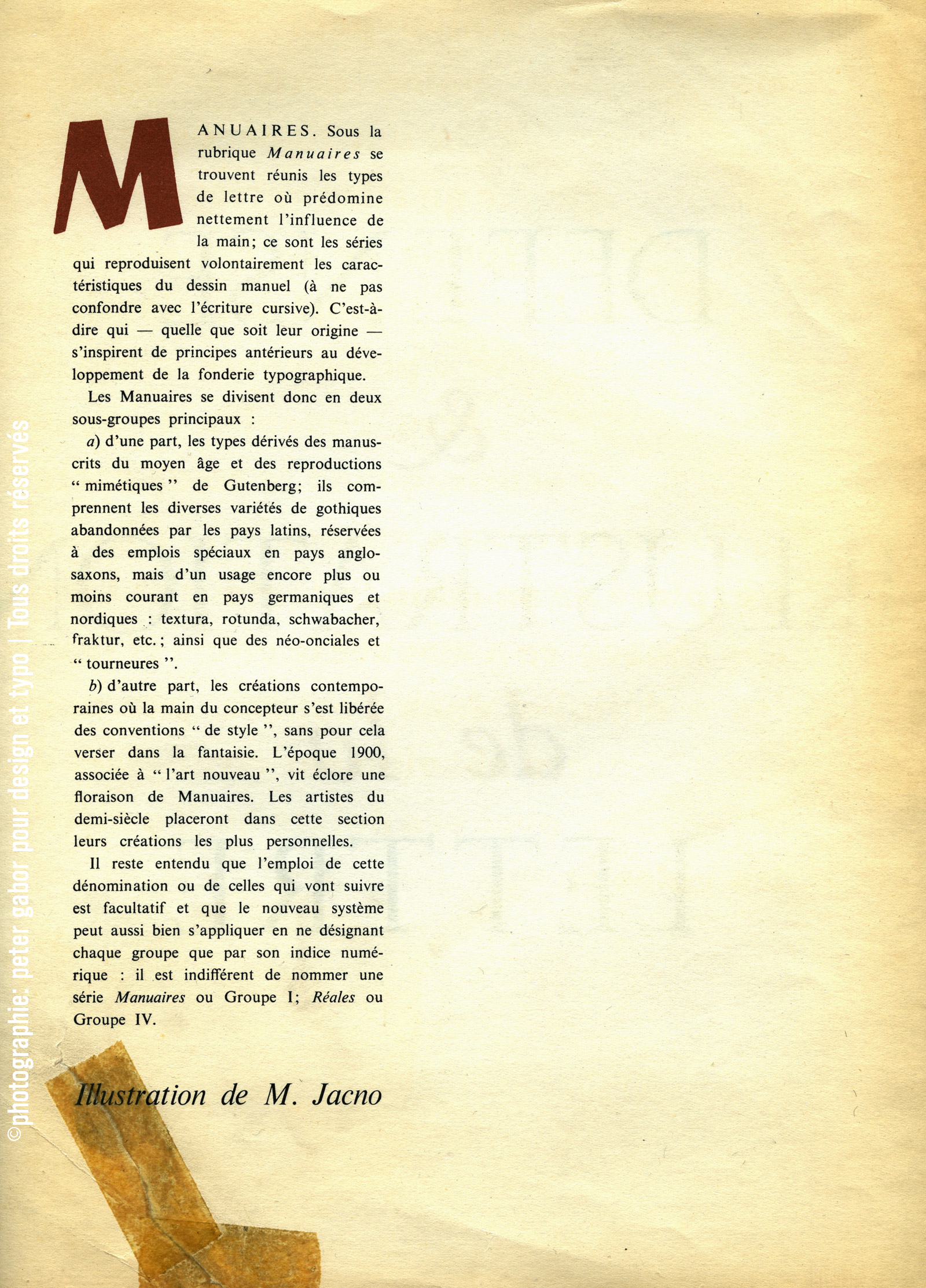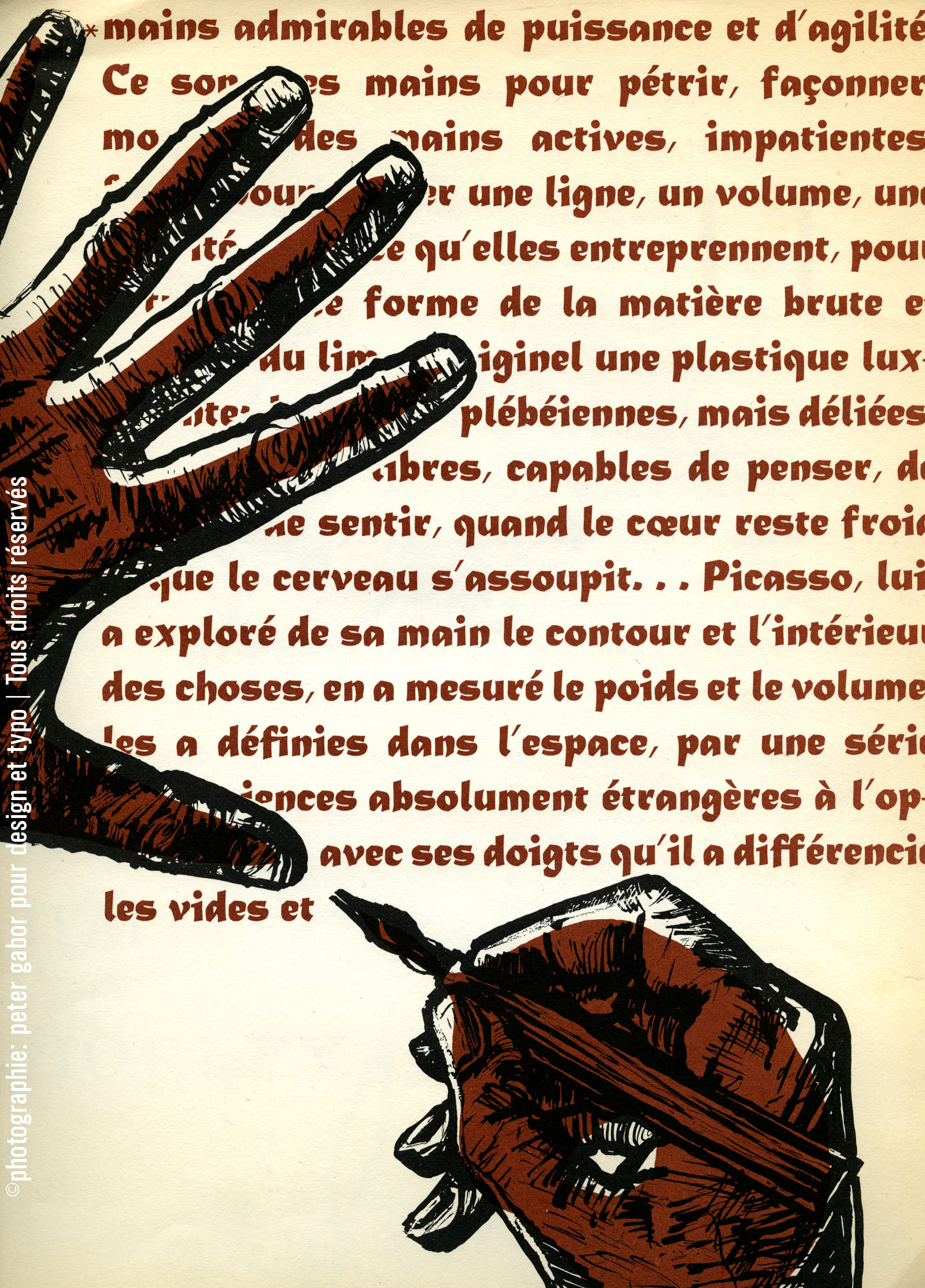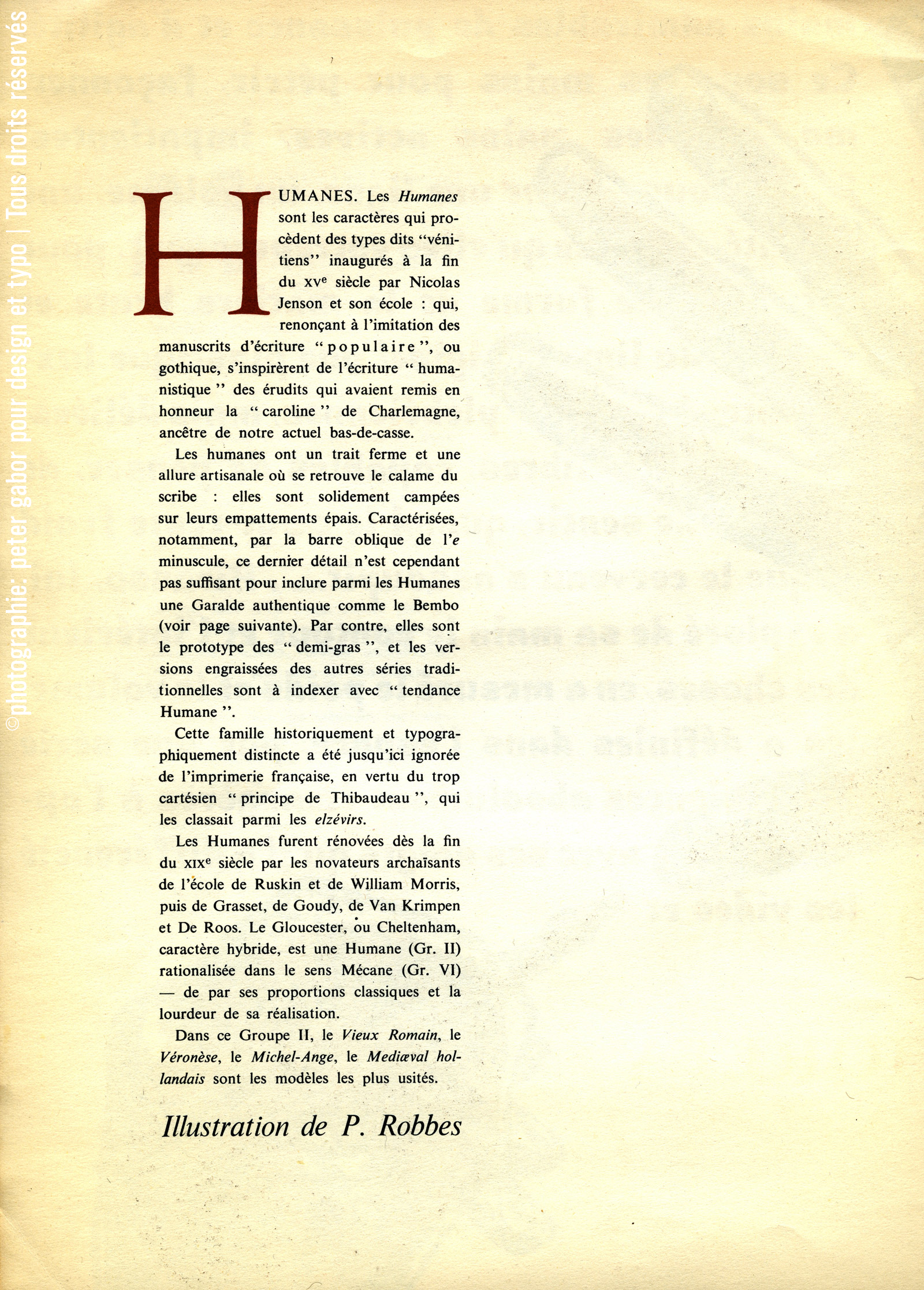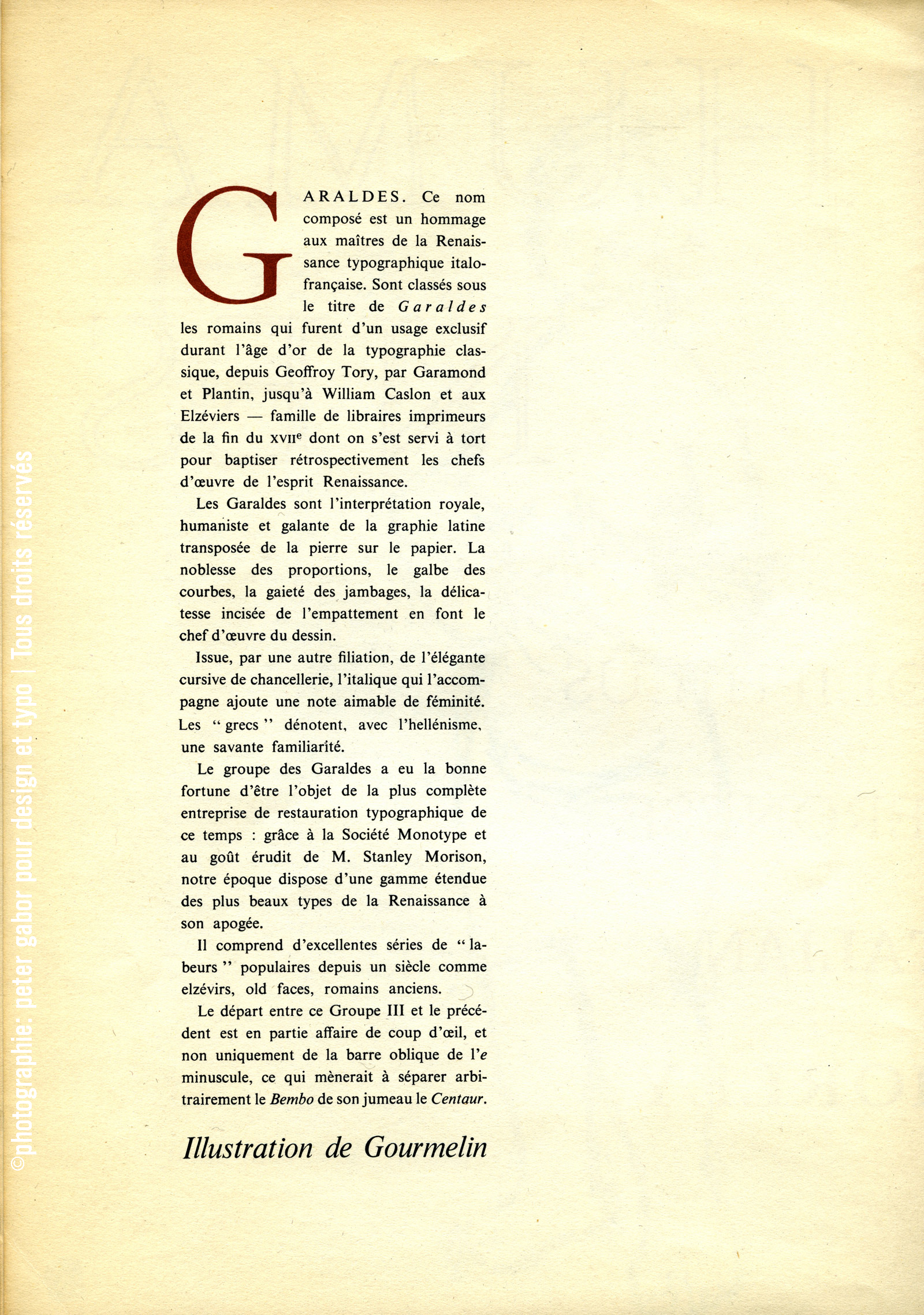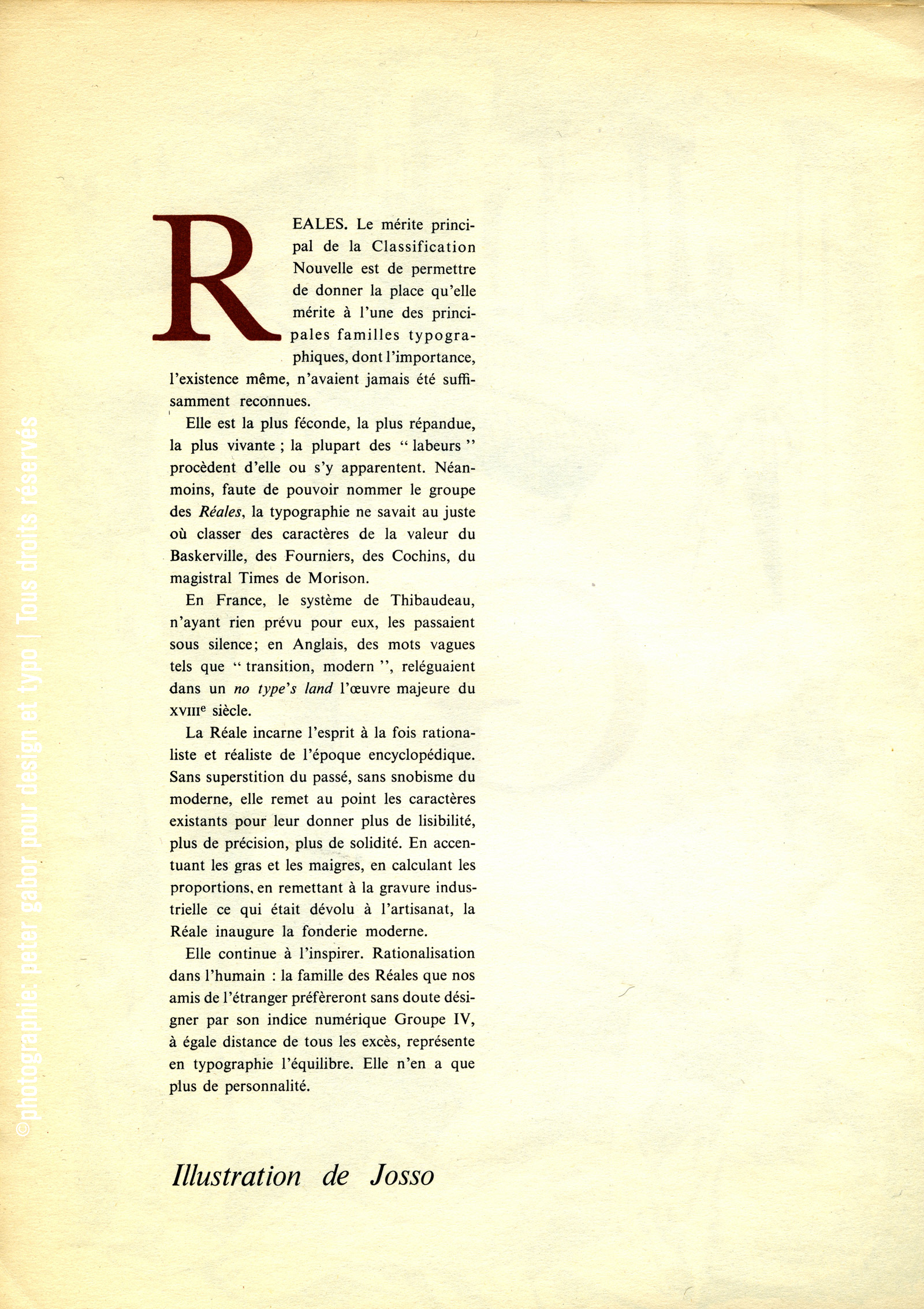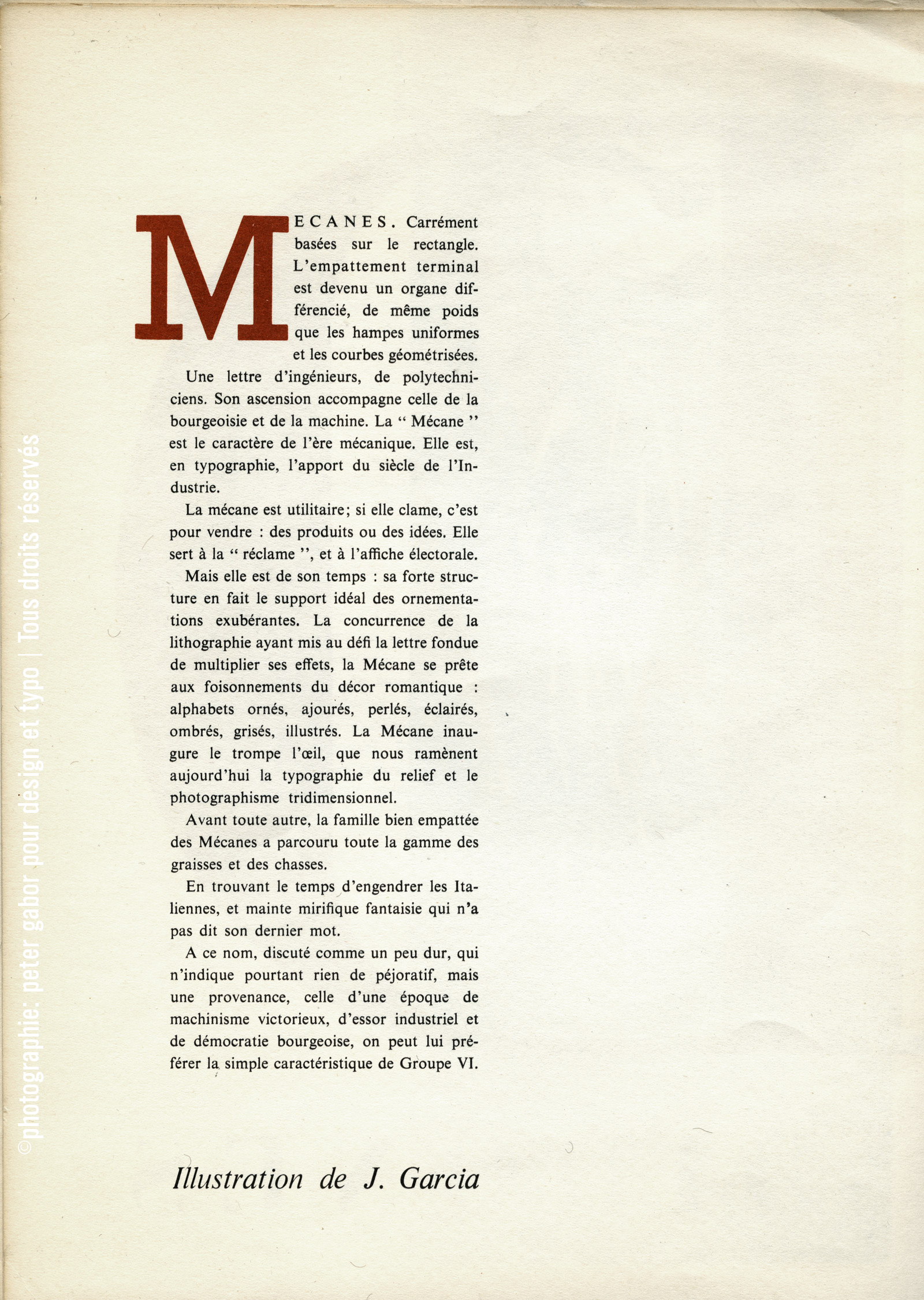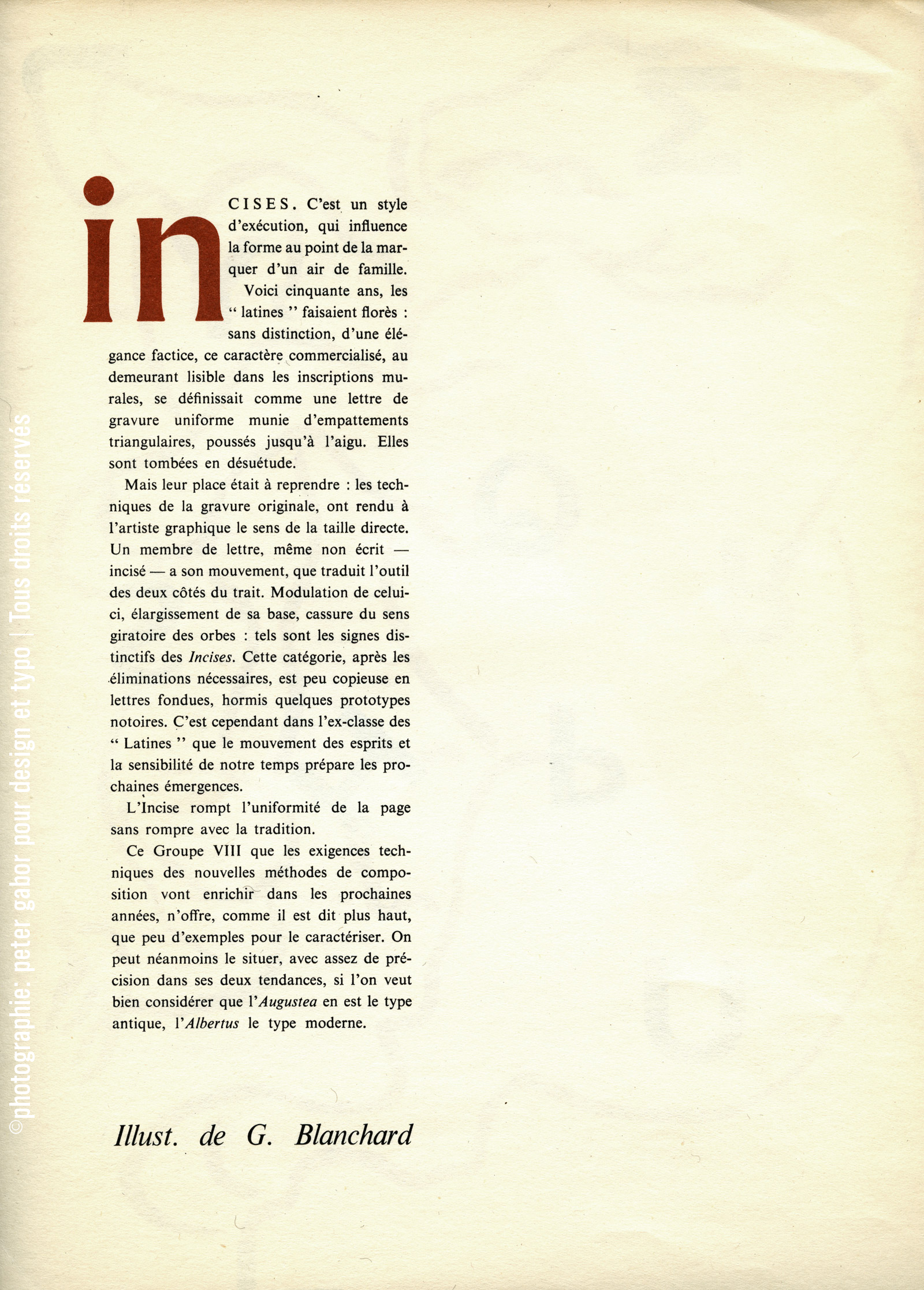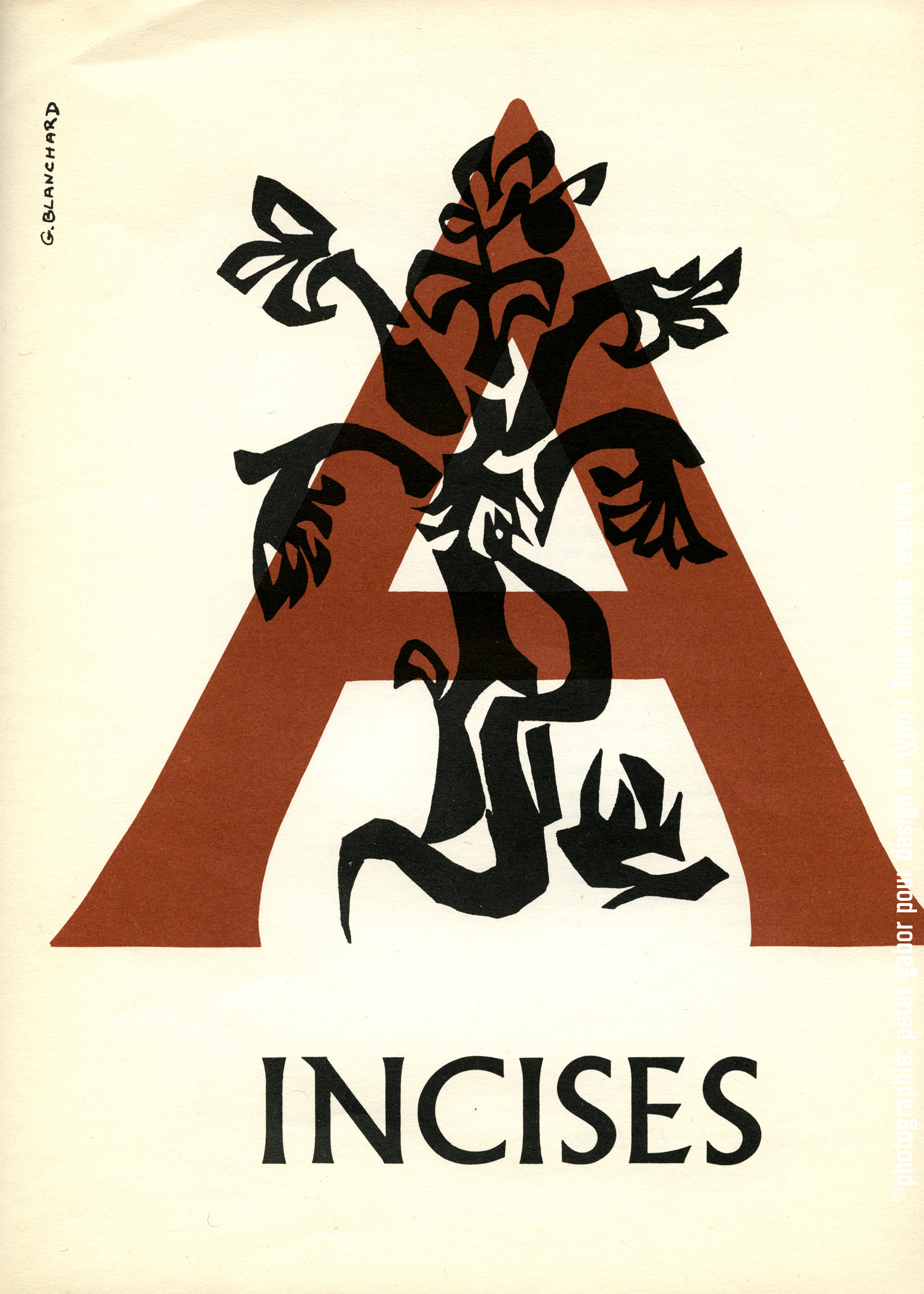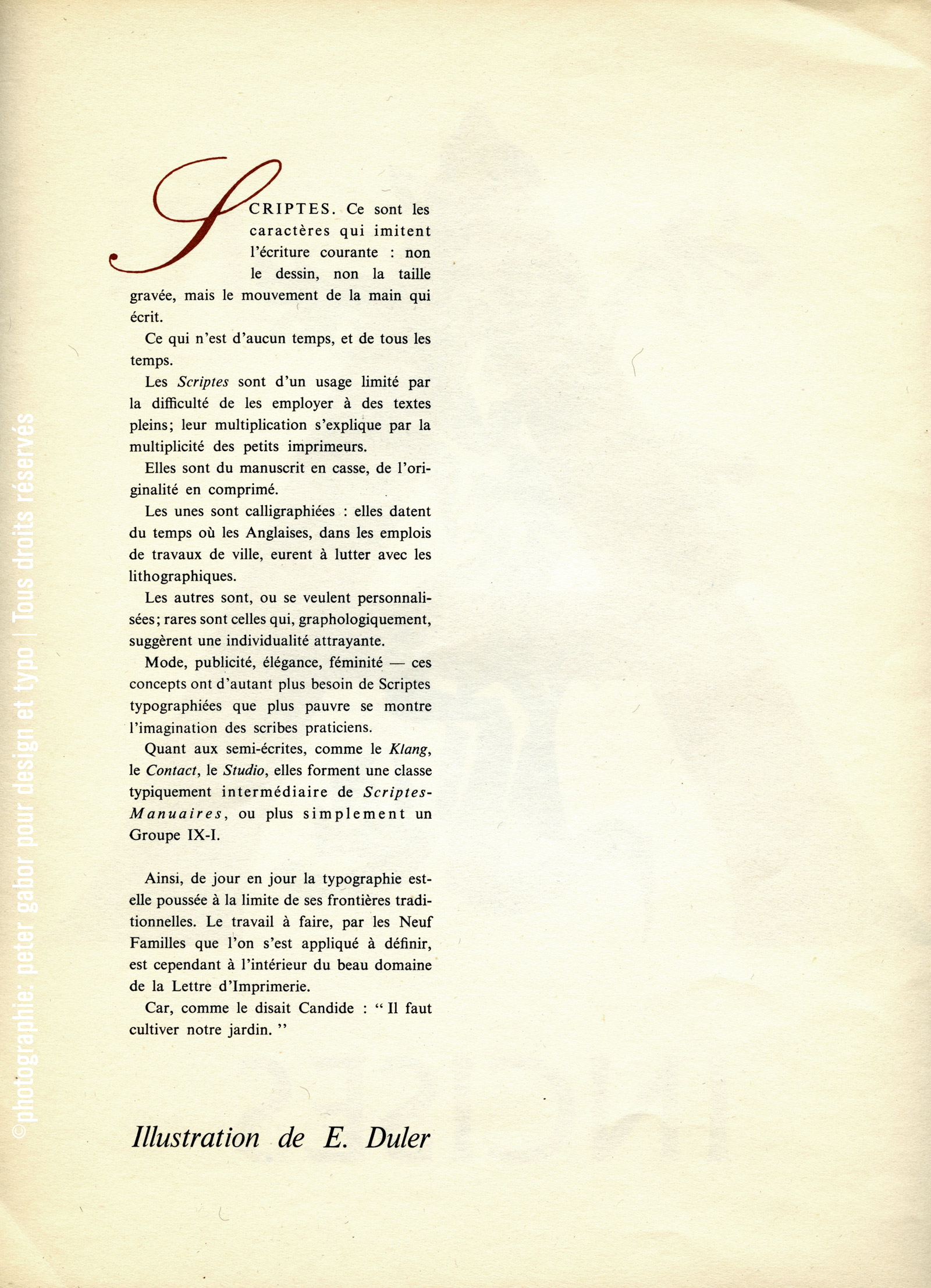
Typographie et Classification Vox | un des premiers documents publié par Maximilien Vox
Un des premiers documents édité par Maximilien Vox qui décrivait dans le détail l’origine de sa classification.
Publié par la S.A. Monotype en 1955, Maximilien Vox (de son vrai nom Monod, de la famille de Théodore Monod) cet encart fut ensuite inséré dans le Caractère Noël de la même année. On y retrouve notamment des illustrations de Gérard Blanchard, de Jean Garcia et de Jacno (le packaging de la Gauloise). N’hésitez pas à cliquer sur les reproductions, elles sont dans une taille respectable pour que vous puissiez les lire et en apprécier la composition et les illustrations. ©peter gabor directeur d’e-artsup | tous droits de reproduction réservés.